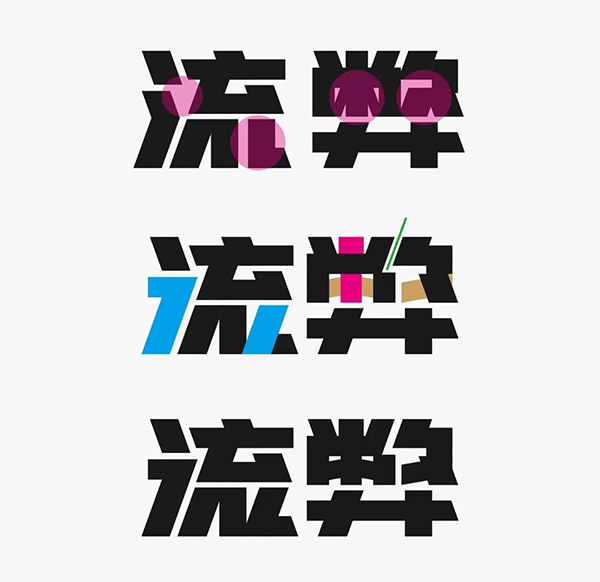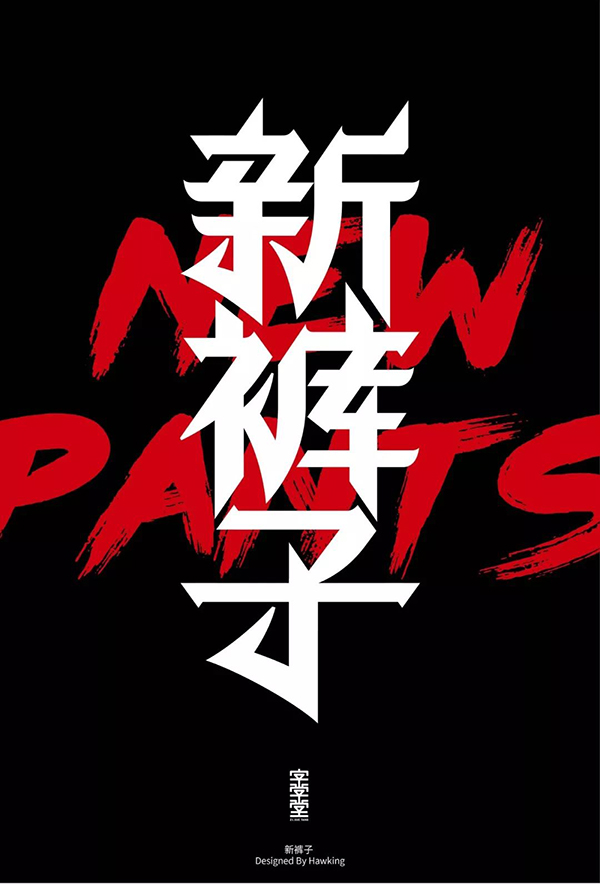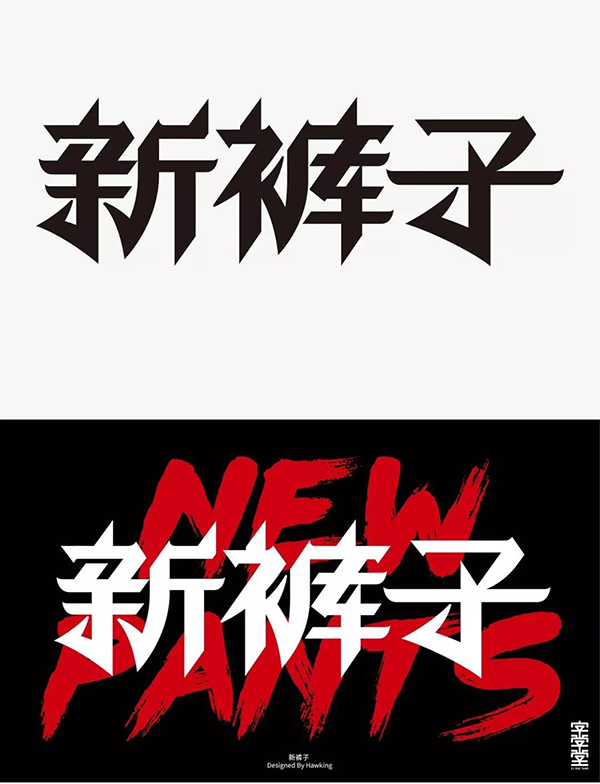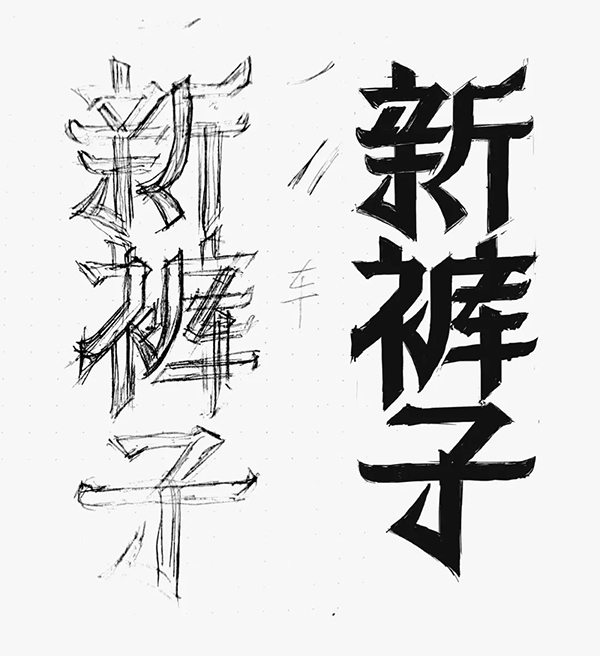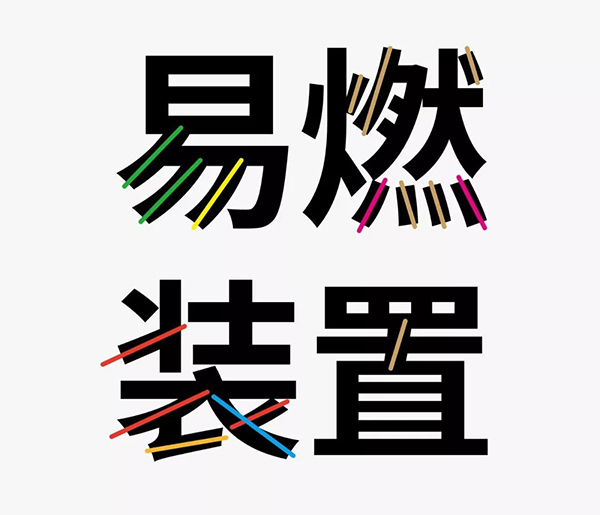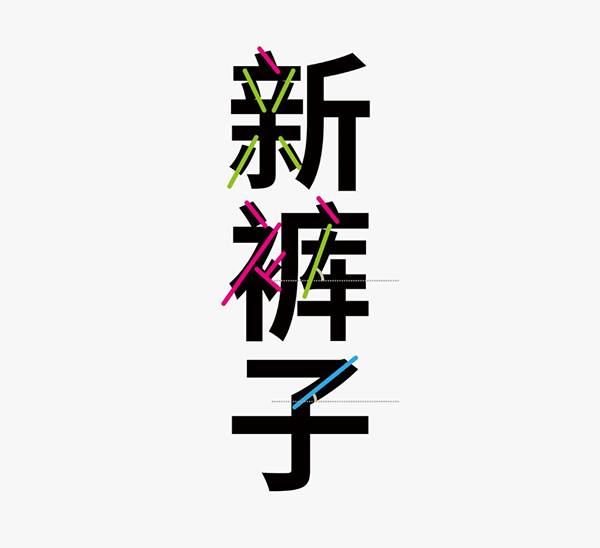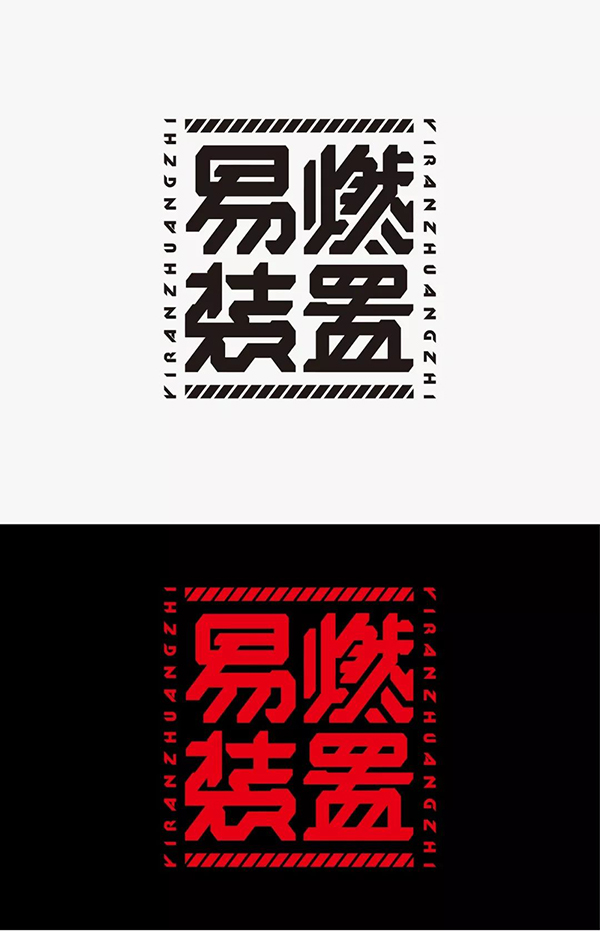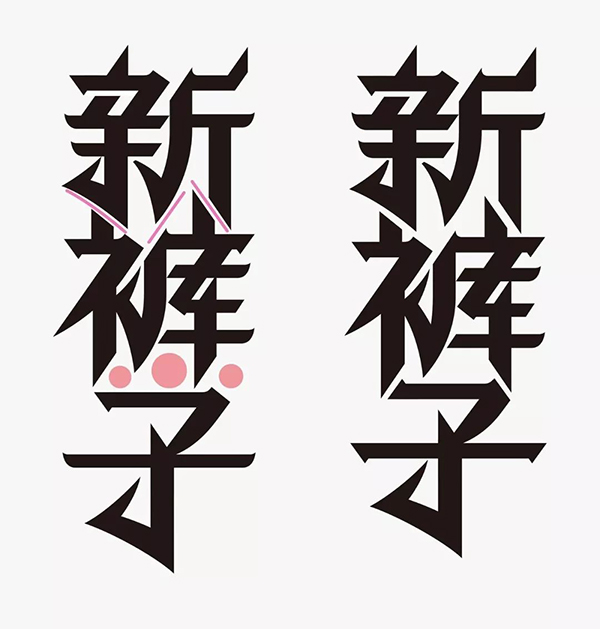
最简单的造字方式大公开字体资讯
论字体设计的方法有很多种,本次将向大家介绍一种最简单易用,且效果出众的造字方法:统一斜线造字法,顾名思义字形中出现的所有斜线倾斜度都要保持一致,这种做字方式在日本的字体设计作品中是很常见。如下图可见,只需做到将所有斜线保持统一倾斜度后,设计出的字形的设计感会自然形成。
基础篇
此方法最重要的是斜线倾角的大小,那么最简单也最易于操作的倾角莫过于45°了,只需按住Shift键即可实现。这与网格造字的规律如出一辙。
我们以“时间饥荒”为例,采用45°倾角的斜线进行设计,在使用此方法做字时,一定要凸显出斜线。先打出字型观察下结构,可以看到前两个字中撇捺笔画较少,也就是斜线类笔画较少,为强调出斜线特征,需要对他们的结构进行调整才行。
先从前两个共同含有的“日”字形结构的字下手,采用描边方式进行设计。以“时”字为例,通过对“日”字形斜切的方式,来增添斜线结构,其最后一版为增强斜线特征进行了笔画延长,点画的调整是为使笔画负空间得以饱满。
接着按照这样的规则,将其余的三个字一并制作出来。其中对包围型结构“间”字内部“日”字形的笔画宽度进行了微调,并注意下字形内部的负空间与字间的负空间是如何处理使其达到饱满这一效果的。在制作时不要做形状的修剪,可先用白色形状添补即可,这样会方便后期的修改。
在基本字形制作好后,为进一步增强斜线特征,对字形顶部的斜线也做外延处理,并将底部切齐。
整体调整时,对字面进行了内收,并对“时”字进行微调,以增强内部饱满的程度。
最终,搭配上一款无衬线体的西文字型,这组字形的设计就此完成。可以看到整体字形斜线特征很强烈,并且有些笔画为达到统一斜线的效果,对结构进行了调整,在做结构调整时一定要注意是否影响到了字体识别度。
提升篇
斜线倾角除45°之外,还可选用其他角度,那么这就要根据不同的字形灵活设定了。我这里选用最近比较入门的综艺《这就是街舞2》中的一支战队“易燃装置”为内容进行设计。
首先要确定出斜线倾角,大致将这几个字中的撇捺笔画用斜线标注出来,其中颜色相同的斜线意为倾角相同。
将提取出的斜线整理成同一朝向,下面就可从中选取一条适合的斜线了,通常不会选用极值的斜线,也就是倾角最大与最小的斜线。一般会选用中间倾角稍大的斜线,因为倾角偏小时,设计出的字形会比较扁平,当然若是想达到这样效果就另当别论了。但通常情况还是希望设计出的字形高挑些,那么我这里选用黄色这个倾角的斜线。
在设计前同样先观察下字形结构,我们可以先从笔画最多的“燃”字开始,以方便确定字面的大小。可以看到“燃”字的笔画很密集,那么这时就可以考虑使用简化笔画的方式进行设计,简化应遵循就近原则。在下图中标注出了几处该字笔画较为密集的部位,在这些地方是可以考虑进行简化的。
同样采用描边方式将基础字形制作出来,由于笔画较多,其中对个别笔画进行了减细调整,并对上文提到的几处进行简化,其中“灬 ”这样调整是为了字形负空间的饱满。在设计时着重要注意下结构是否正确。
“燃”字基本设计好后,将其他三个字补齐,为进一步强调斜线特征,对“易”与“燃”字的结构进行了调整,其中由于“置”字的横画较多,故对其笔画宽度做了调整。“装”字为保证斜线的一致性,简化处理后的字形,由于存在某些相同结构的重复,使得该字看起来会比较统一。
这样基础的字形设计的差不多了,为进一步体现出机械的视觉效果,需在基础字形上做体势的修饰。
通过对机械装置的参考,以增多笔画棱角与体饰的方式来增强机械感。
调整前后的直观对比图。
但“燃”字底部的笔画有些细碎,有些位置的负空间还有待完善。故针对这两处问题进行调整。
“易”这样简化也并不理想,做了三种调整,最终选取负空间较为饱满且舒服的第二款字形。
经过微调前后的对比,字形灰度明显提升了许多。
最后加入些许辅助元素,以增强形式感。并配以黑、红色,来增强炫酷时尚感。
升级篇
在统一斜线的基础上,可加入些许特异的处理方式,以打破固有的规律,来增强字形的灵动感。这里以“流弊”为例,首先同样将所有的斜线笔画标注出来,由于字数较少的关系,可以从这些斜线中选倾角相同且数量最多的为统一斜线的倾斜度。如下图中蓝色的斜线。
这样就可以先将笔画的宽度与倾斜度确定出来,注意使用矩形方式做字时,斜线需要适当的加粗。
以上准备好后就可以开始做字了,其中由于“弊”字上半部分的笔画较多,要对笔画宽度进行调整,以达到黑白空间的协调。
目前初步设计出的字形,统一斜线的特征还不是很强烈,下面对“流”字的调整主要是增强斜线特征。“弊”字上半部分结构还是有些拥挤,内部斜线可换用横画做倾斜,那么这就会引入了第二种倾斜度的斜线,并且为增强笔画间的互补关系,又做了类似断笔的处理,这样调整使得“弊”字的灰度与“流”字搭配起来协调了许多。
再对“流”字细节进一步微调后,该字形就此设计完成。
在加入特异斜线笔画时,斜线的倾角不宜过多,这样会破坏统一斜线的规律感,以至于无法体现出统一斜线的特征。最好是加入的特异斜线的倾斜度也是一致的,如该字形的设计。
终极篇
特异笔画除了直线外,还可加入曲线,一旦有曲线的加入字形设计的难度就会递增。
以“新裤子”为例,为方便大家更准确的抓住字形特征,提供了一个字形作品作为参考。可以看到该作品含有哥特体的特征,先来分析下:
1、结构规律,可以观察到字形中使用的斜线倾斜度都是一致的,也就是统一斜线的做字方式。
2、在字形底部加入曲线形态,以打破固有的规律感,并强调出特异的曲线笔画。
3、笔画的造型特征,其中最具特点的是竖弯钩的处理方式。
我们大致将作品分析清楚后,下面可以开始作字。
首先统一所有的斜线,下图我将字形中所有的斜线都标注出来了,需要将这些斜线的倾角统一。若采用倾角最小的斜线(蓝色),那么设计出的字形会比较扁平,这并不是我所想要的;其中有几条斜线的倾角度数很相近(绿色),可选用这一倾角的斜线进行设计,并且在不大面积破坏字形结构的基础上是可以将所有斜线达到统一的程度。
鉴于字形比较复杂,除了要统一斜线,还要在字形底部融入曲线形态,故先绘制出下图的草稿,可以看到它完全满足参考字形的特点,并加入了自己的理解。
先从笔画较多的“裤”字做起,按草图制作出的字形并不是很理想,“衤”相较于右侧“库”的灰度明显失衡,并对间架结构与竖画做了优化与规范。
“新”字也不是很理想,连接简化的处理方式有些刻意,并且简化后笔画不够紧凑,负空间明显失调,改用“裤”字的处理方式后,字形显得更加整体统一了。
竖排后为使字形更整体紧凑,对“裤”字底部做调整,以增强字间的互补关系,但“子”与“裤”字间的负空间不够紧凑,故对笔画形态进行调整。
而后对笔画密集处的笔画宽度进行微调,并且统一折线笔画的斜切角度。
最终设计完成的模样。
另设计出一版利于应用的横排用字,注意其中对“子”字的微调。加入曲线特异笔画时,同样要有一定的规律,如该字形曲线笔画全部集中在字体的下半部分,并且形态相似,这样设计出的字形在富有变化的同时又不失规整感。
总结
“统一斜线”这种做字方法,原理非常简单,只需将字形中出现的斜线笔画,统一为一个倾斜度即可,可是为满足这一特征有时会对字形结构进行调整,这样也就提高设计的难度,但这种设计方法的魅力就在于设计出的字形是独特的。
在设计前先要确定斜线的倾斜度,有两种方法:1、选用中间值的倾角且度数稍大的斜线为统一斜线的倾斜度。2、选倾角相同且数量最多的为统一斜线的倾斜度。
设计出的字形要凸显斜线特征,否则就失去了使用此方法的意义;字形负空间要调整饱满;在加入特异笔画时要有一定规律;不要一味追求斜线的一致性而忽视字体的结构,要做到二者兼得。
此方法是原理最简单的一种做字方式,设计出的字形会自带设计感,但还是有一定的难度,一旦掌握后,会助你一臂之力!